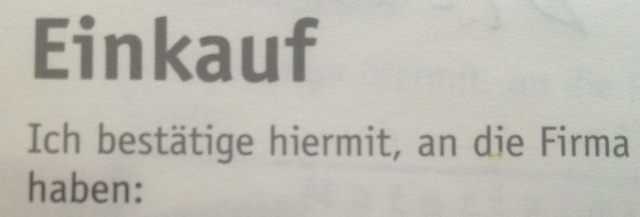
Kennt irgendjemand diese Schrift?
ich suche eine bestimmte Schrift, die der Meta sehr ähnlich ist, doch das kleine i hat so einen Haken nach links.
Kann mir da jemand weiterhelfen?